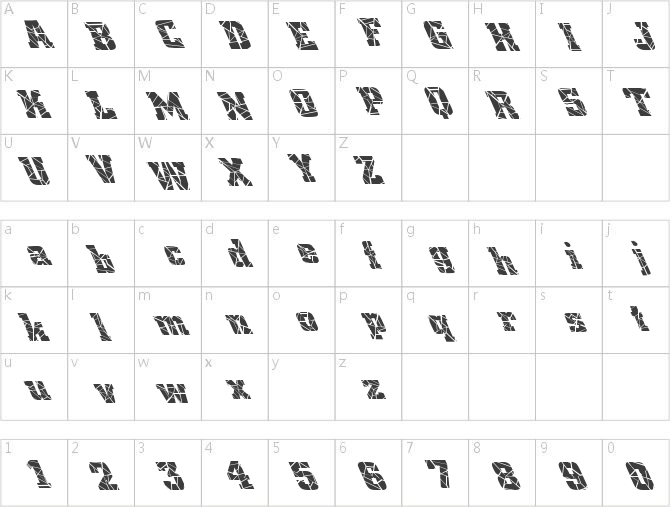
FZ BASIC 53 CRACKED LEFTY
FZ BASIC 53 CRACKED LEFTY字體字庫(kù)是一款讓人賞心悅目、百看不厭的英文字體,適合各類廣告和產(chǎn)品包裝設(shè)計(jì)應(yīng)用,字體大小0.09MB,格式為ttf字體,上傳用戶是happy,作者/版權(quán)方為未知